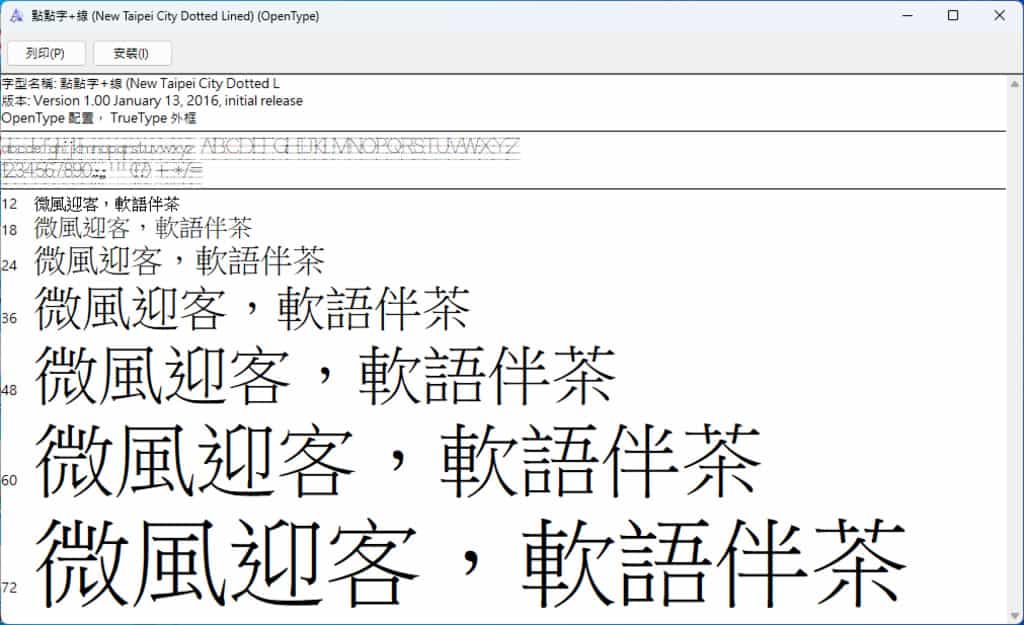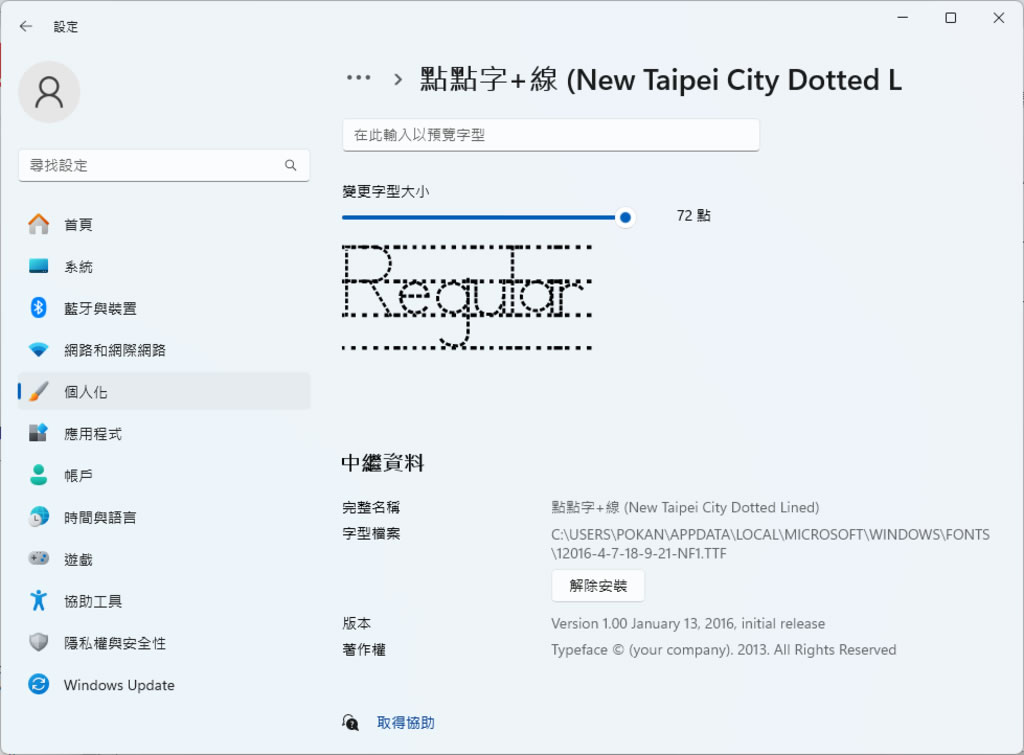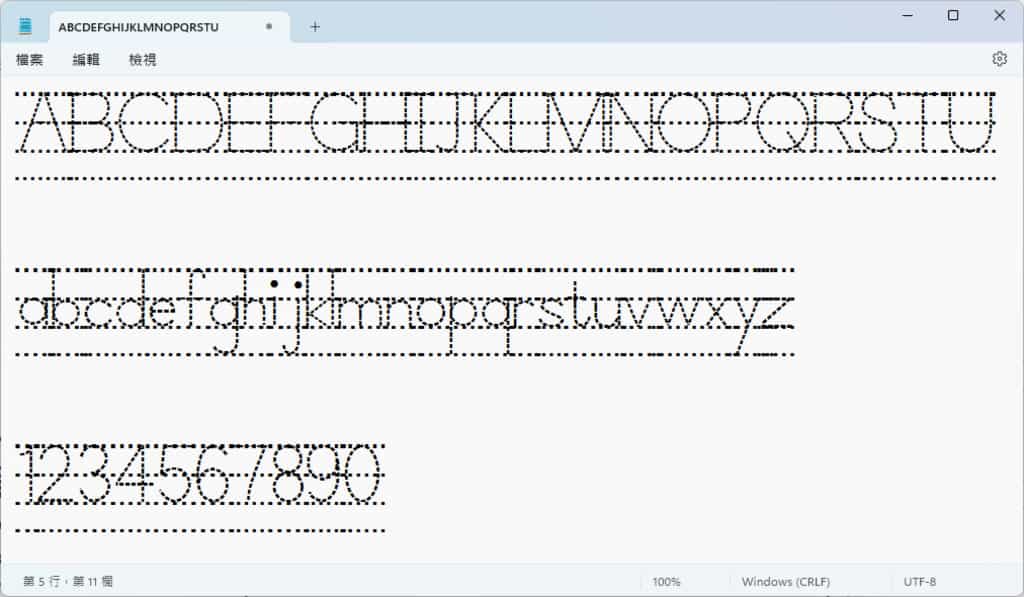
新北市免費英文字母描寫字型下載!點點字、實心字、空心字,正確學習輕鬆搞定
透過描寫是很多初學寫英文字母與阿拉伯數字的有效途徑,市面上也可以購買的到搭配四格線的點點字或是空心字等作業簿,用以協助學習者熟練書寫技巧。而想要多練習正確的英文字母及數字寫法,除了學校所發的作業簿本外,還可以利用新北市自行研發的英文字母及數字描寫字型自行列印。這套字型提供包含「點點字」、「點點字+線」、「實心字」、「實心字+線」、「空心字」與「空心字+線」等六種教育字型,使用者可以根據程度自行下載安裝使用,提供更多彈性的學習選擇。